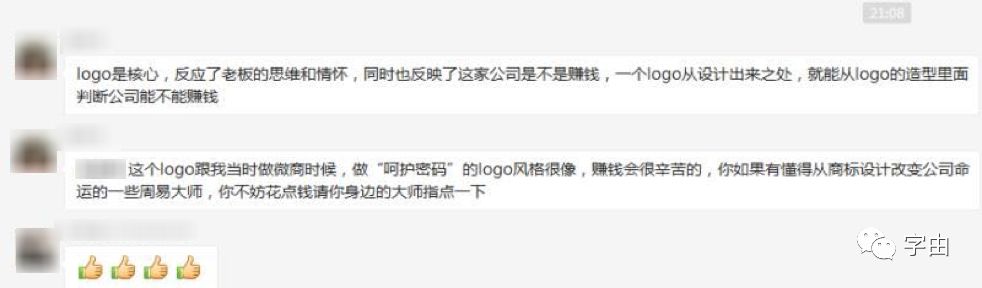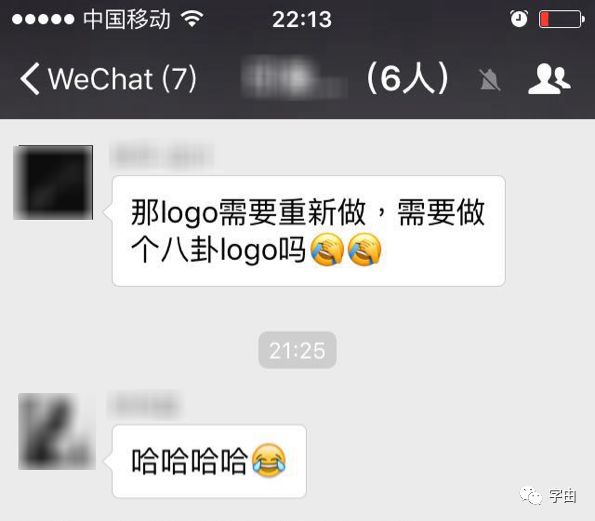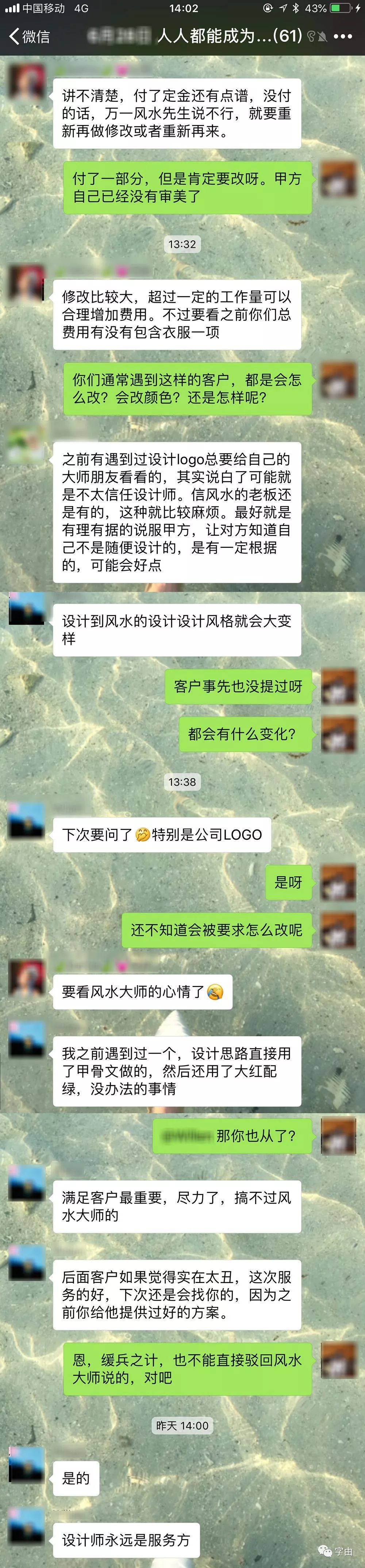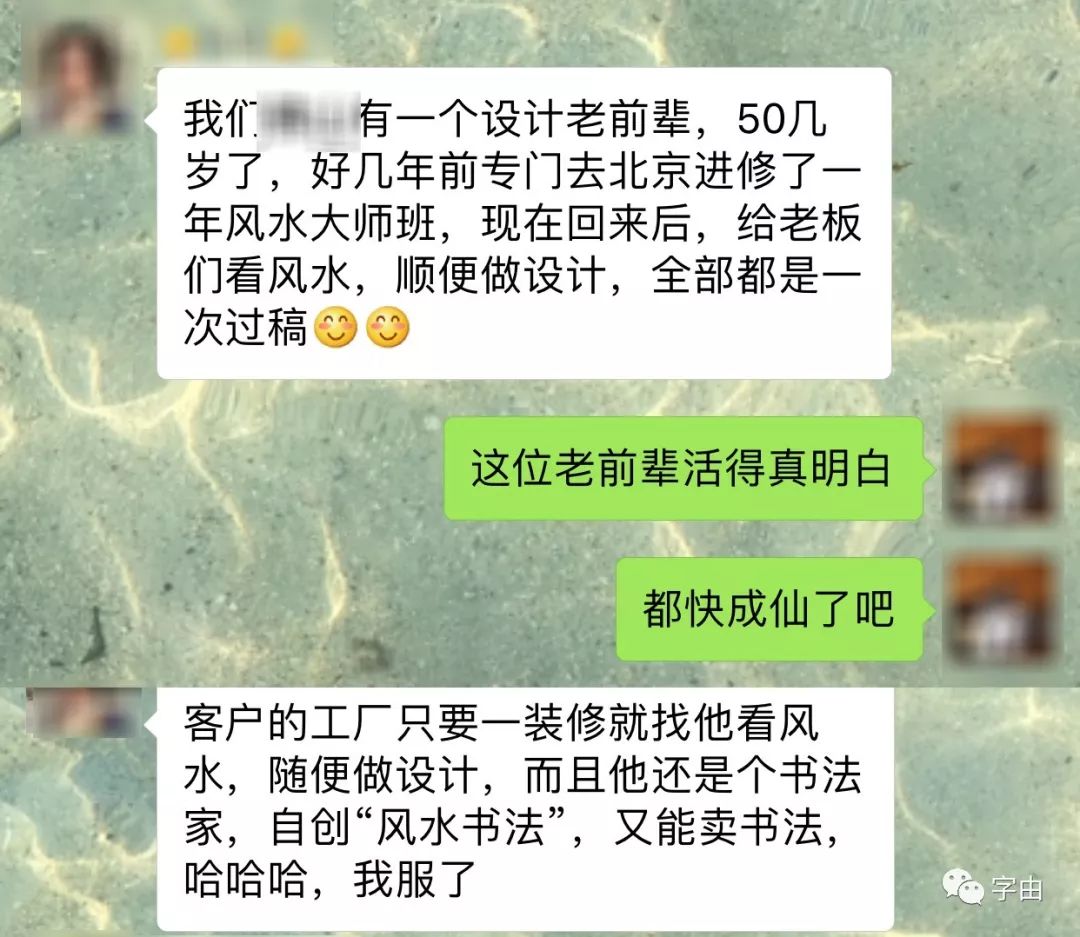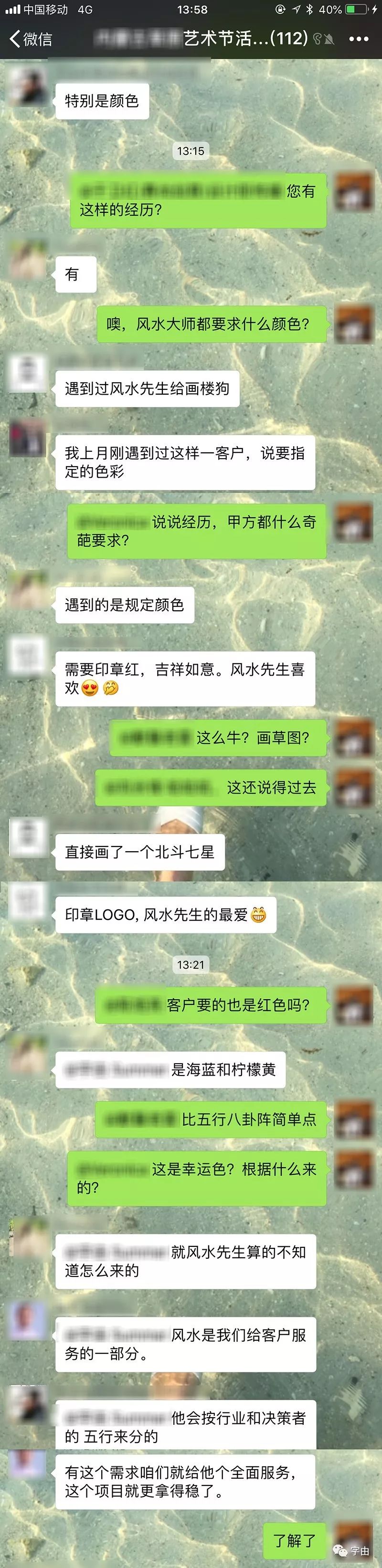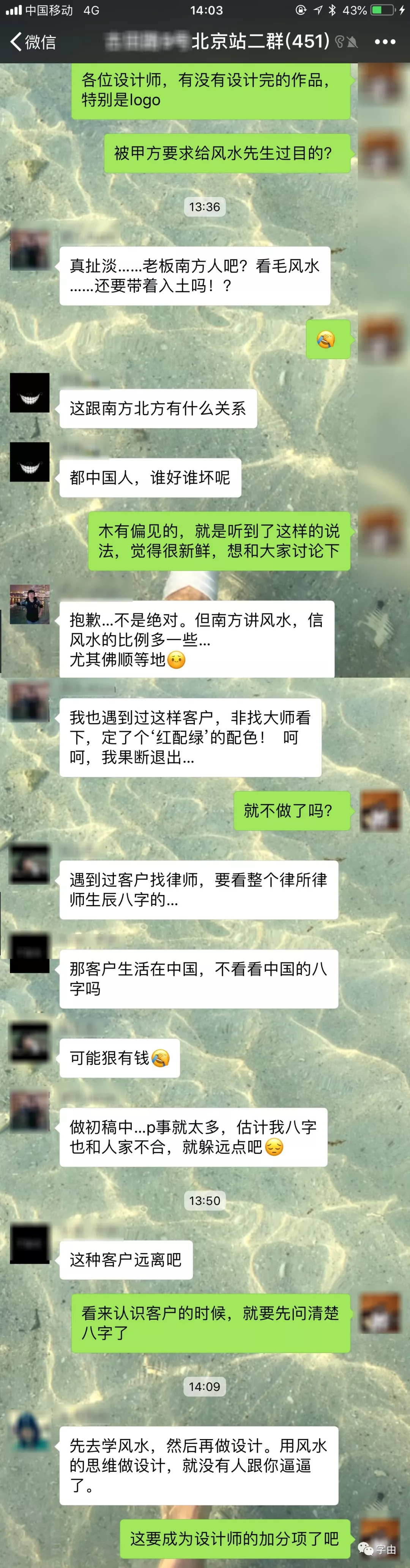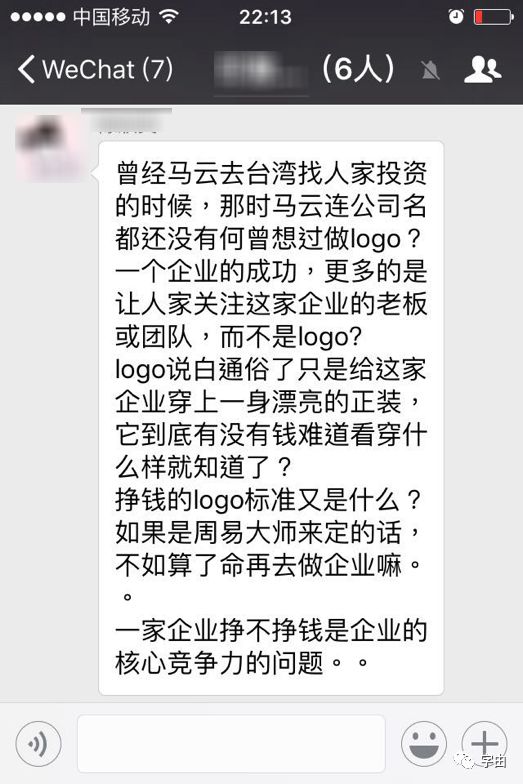
Logo好了吗?风水先生到啦
就没遇过这么奇葩的!
相信不少设计师朋友会遇到这样的客户——总是喜欢把设计师做好的LOGO交给所谓给风水先生过目,
让风水师来确定LOGO的可行性。
还有这样的事
作为设计师的我们只能
八卦也行吗?
真的???????????????????????????????????????
甲方要求看风水的话题真不是个别现象,
小编到一些群里撩了一圈,真是大开眼界。
客观的说,“红配绿”也不是不好看
(咬碎了牙往肚子里咽),
圣诞红和圣诞绿、敦煌的土红粉绿,
选好纯度色相,搭配起来也会很好看。
(多么积极正向的自我安慰)
为了满足客户的奇葩需求,设计师们也是绞尽了脑汁。
虽然选颜色的依据说不清楚,但是客户的需求一直存在,不能硬顶,
那么就把需求变成服务的一部分。
上面说到的这位真是佩服,太具有开创精神了。
设计师的工作领域越来越宽了,不止提供设计表现,
还要满足客户心理上的诉求。
嗯!这位妹子说得好像还有点道理!
同意不?
话说这种经过风水大师来确定Logo的事在某些品牌上是否也发生过呢!
还记得你经常光顾的那家士多小店吗?
知道为什么7-ELEVEn最后的n为小写,其余英文为大写吗?
此种设计的原因,是因为在华人地区(尤其是台湾)的民间说法是因为风水的因素:
大写N的最后一划为往外,表示会将钱财散出去,而小写n的结尾为往内,表示会吸引钱财进来。
这下知道为什么7-ELEVEn后面的n是小写的了吗?
是感觉又涨知识啦 !
lalalala~~~ 小编也没闲着,发现了一些小捷径,
简单总结一些常用的小知识给大家。
是时候来小段Freestlye 66
Logo这点事何必苦苦恋
先生说不好向谁去喊冤
问你何时曾看见
甲方爸爸为了设计师而改变
选字问题也一样
有了上面的小方法
大家在设计日常中是否也会遇到这样的情况呢!